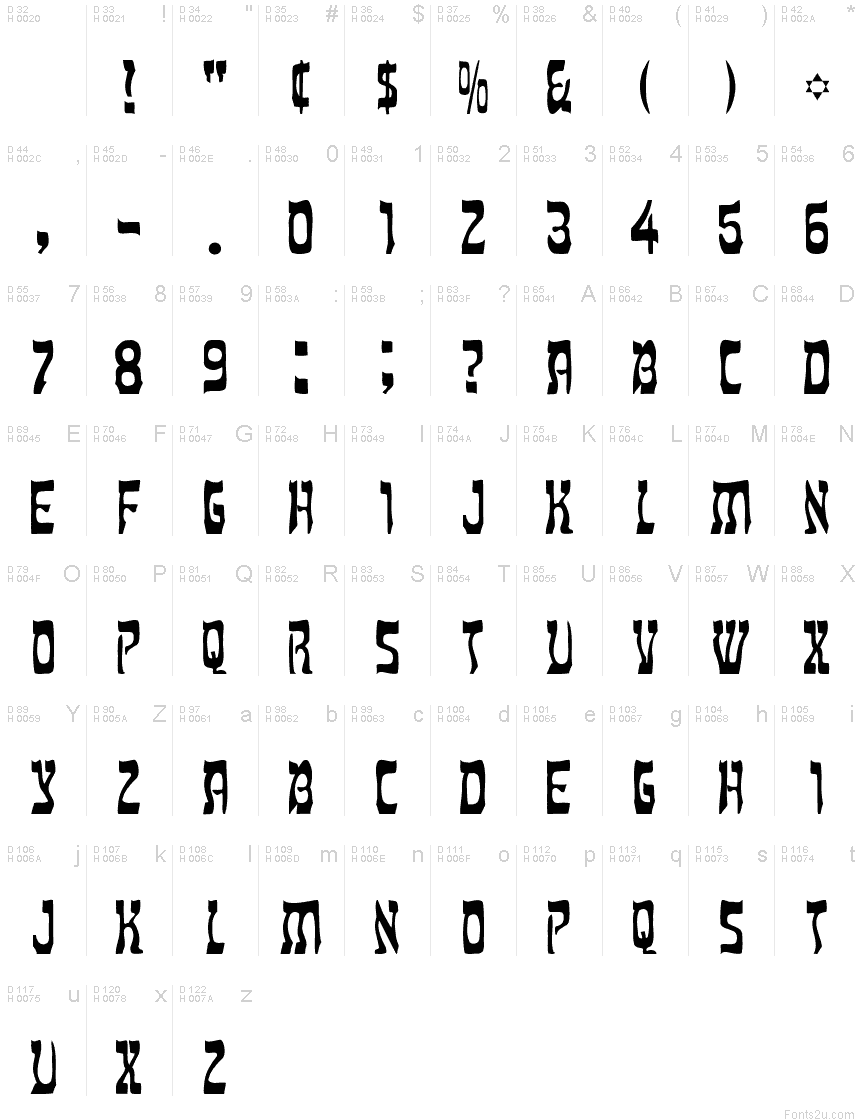
Moses Light to darmowy, hebrajski font typu display, którego wysokie, zagięte do wewnątrz kształty tworzą sylwetkę przypominającą wykutą w kamieniu tablicę. Litery zdają się być ściśnięte w wąskich pionowych komorach i szerokich górnych pasach, co nadaje całemu krojowi podniosły, archaiczny charakter, zamiast jedynie dekoracyjnego efektu.
Sprawia to, że jest to naturalny wybór na plakaty o tematyce biblijnej, ulotki synagogalne, materiały na Pesach, tematyczne okładki książek czy tytuły, które wymagają nawiązania do Starego Testamentu bez uciekania się do imitacji kaligrafii. Kompaktowe wnętrza znaków i wyraziste górne krawędzie sprawiają, że świetnie sprawdza się w krótkich nagłówkach, logotypach i na opakowaniach, gdzie historyczny hebrajski klimat jest ważniejszy niż skład tekstu ciągłego.